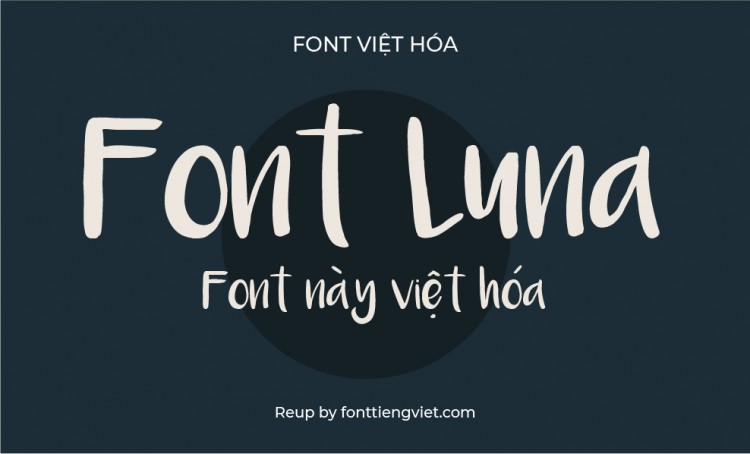
Font việt hoá LNTH Luna
Tải Ngay Font việt hoá LNTH Luna – Font Chữ Viết Tay Tuyệt Đẹp Cho Học Sinh
Giới thiệu về Font việt hoá LNTH Luna
Trong thế giới thiết kế đồ họa, việc lựa chọn một Font Miễn Phí chất lượng luôn là ưu tiên hàng đầu của các bạn học sinh và giáo viên. Font việt hoá LNTH Luna là một bộ phông chữ mang phong cách script viết tay mềm mại, đầy nữ tính và hiện đại. Được tối ưu hóa hoàn toàn cho bảng mã tiếng Việt, bộ font này giúp loại bỏ hoàn toàn lỗi hiển thị dấu khi soạn thảo văn bản hay thiết kế slide bài giảng. Đây là sự lựa chọn hoàn hảo để làm mới các bài thuyết trình, thiệp chúc mừng hoặc các dự án sáng tạo cá nhân tại trường học.
Đặc điểm nổi bật của Font việt hoá LNTH Luna
Thiết kế mềm mại và linh hoạt
Bộ Font việt hoá LNTH Luna sở hữu những đường nét thanh mảnh, uốn lượn tự nhiên như nét chữ viết tay thủ công. Điều này tạo nên cảm giác gần gũi, thân thiện nhưng không kém phần chuyên nghiệp. Font chữ này rất phù hợp để trang trí tiêu đề bài học hoặc làm nổi bật các ý tưởng quan trọng trong bài làm nhóm.
Khả năng tương thích cao
Cách ứng dụng Font việt hoá LNTH Luna hiệu quả
Để tận dụng tối đa vẻ đẹp của Font việt hoá LNTH Luna, người dùng nên kết hợp nó với các font chữ không chân (Sans Serif) đơn giản để tạo sự cân bằng. Việc sử dụng font này cho các câu trích dẫn hoặc tiêu đề trang bìa sẽ giúp nội dung trở nên thu hút và dễ ghi nhớ hơn đối với người xem.
Kết luận về bộ font chữ độc đáo